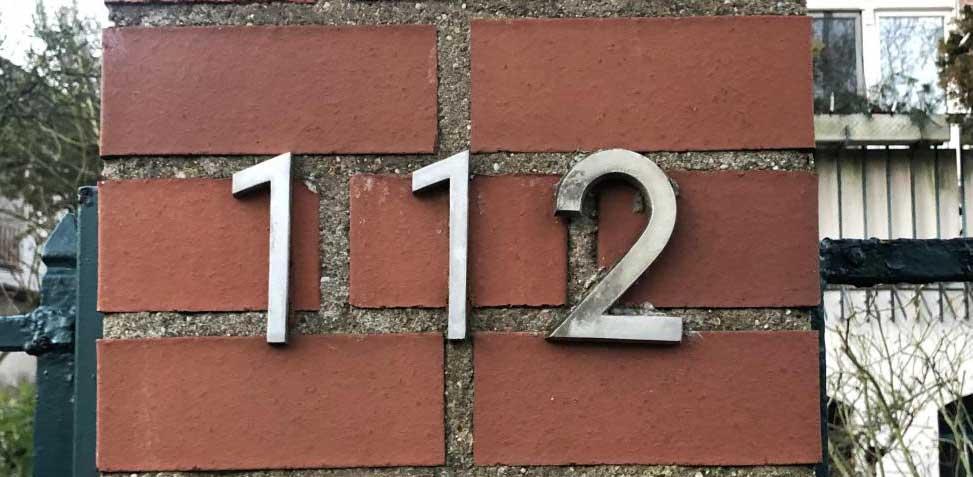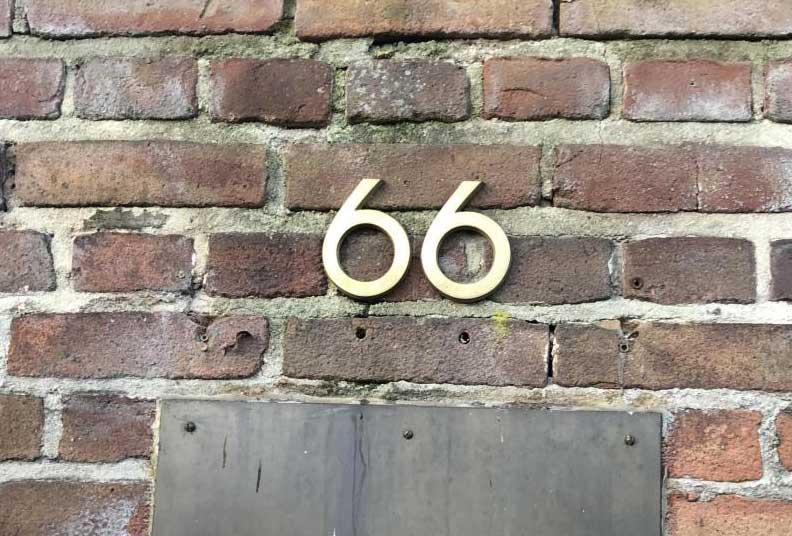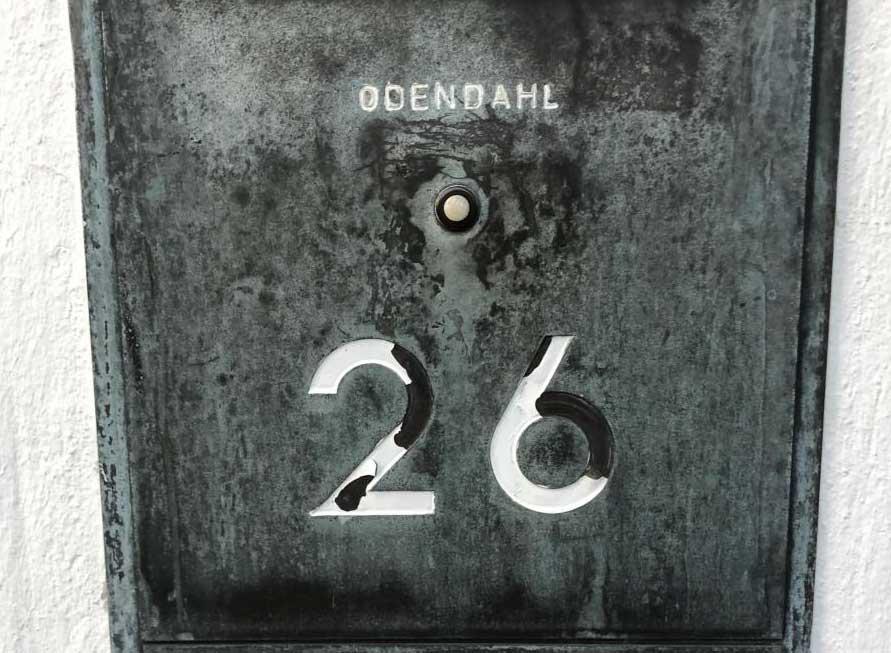
Suche die Schriftarten von Haus-Nummern aus den 20er Jahren
ich bin auf der Suche nach den Namen der Schriften, aus denen die Hausnummen sind, die ich unten angehängt habe. Wir suchen für unsere eigenes Haus bzw. unsere Hausnummer (das ist die ‚1’) eine Schrift, die aus der Zeit um 1922 (oder früher) gebräulich war. Die Nummern, die ich fotografiert habe, sind aus der Nachbarschaft und von Häusern, die auch in dieser Zeit gebaut wurden. Ob die Hausnummern neueren Datums sind, weiß ich allerdings nicht. (Ich habe noch eine andere Hausnummer fotografiert, die kann ich leider aber nicht hochladen, weil der Speicherplatz nicht reicht) Falls ihr nicht wisst, wie diese Schrift unten heißt, habt ihr dann eventuell einen Tipp, welche Schriftart wir verwenden könnten, die ganz ähnlich ist? Danke im Voraus für Eure Hilfe!
Dieses ist die dritte Hausnummer, die wir von der Schriftart schon und passend finden würden! LG Ellen
Wurde die Futura nicht erst nach 1922 veröffentlicht?
Die Neuzeit von 1928 (eigentlich auch zu spät) hätte eine hübsche 1 …
Ja, natürlich. Die ausführliche Antwort wäre wie immer: Schrift auf Häusern wurde damals in aller Regel nicht aus Satzschriften erstellt. Somit gibt es keine Schrift mit einem bestimmten Namen zu identifizieren. Es handelt sich um Einzelanfertigungen. Ähnlich wären …
Ich bezog das auf
eine Schrift, die aus der Zeit um 1922 (oder früher) gebräuchlich war.
Ziffern dieser Art wurden mit Lineal und Zirkel konstruiert und dann als Massenware über den deutschsprachigen Raum verteilt. Man kann den Geist des Bauhaus erahnen? Richard Neutra aus Wien war einer der Verursacher. Diese Ziffern gaben übrigens vor einigen Jahren die Anregung für die Schrift Neutraface.
Typeface:	Neutra Text
Designers:	Richard Neutra and Christian Schwartz
Year:		2002
Publisher:	House Industries
Influenced by:	Avenir
Da uns die ‘1’ bei der Futura uns nicht ganz so gut gefällt, wird es entweder wohl die ‚Neuzeit‘ oder die ‚Kabel‘ werden. (Die ‚1‘ der Kabel kommt der ‚112’ auf dem 1. Foto sehr nah, fand ich).